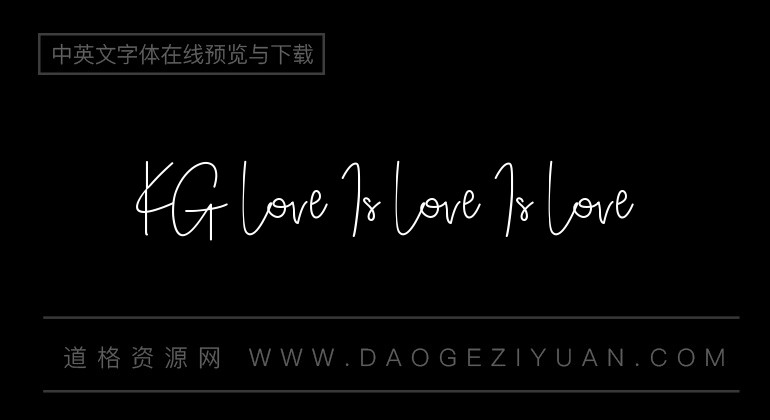
KG Love Is Love
KG Love Is Love 是一种手写风格的字体,由美国设计师 Kimberly Geswein 创作。这种字体的特点是非常自然、随性和亲切,适合用于情人节、婚礼等浪漫主题的设计。KG Love Is Love 字体的字母形状流畅,有些字母还带有心形装饰,整个字体给人一种非常温馨、甜蜜的感觉。如果你正在设计一份浪漫的情书、手写的请柬或者其他类似的项目,KG Love Is Love 字体可能非常适合你。
KG Love Is Love是一款非常不错的手写艺术字体,具有很好的视觉感,适合于文化类的宣传设计、商业类品牌的广告和产品包装设计以及个性化文字排版等较多场景。